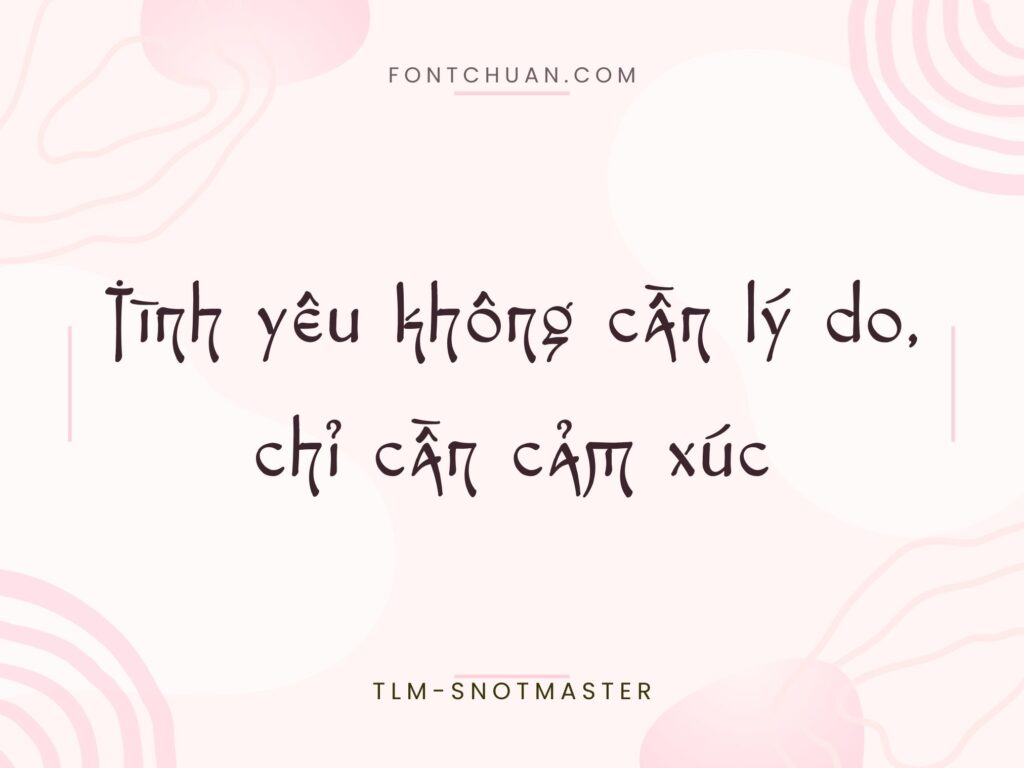
Font Snotmaster V Việt Hóa
Tác giả Font: Walter Velez
Snotmaster V là một font chữ mang phong cách Gothic hiện đại, được thiết kế bởi Walter Velez. Font này có các nét chữ độc đáo, gợi nhớ đến kiểu chữ viết tay với bút lông, tạo cảm giác cổ điển và nghệ thuật. Phiên bản Việt hóa được thực hiện bởi cộng đồng, hỗ trợ đầy đủ tiếng Việt và nhiều ngôn ngữ khác. Font được sưu tầm và đăng bởi thành viên của Font Chuẩn.
Font có thiết kế với các đường nét mềm mại, uyển chuyển, phù hợp cho các dự án thiết kế như bìa sách, thiệp mời, poster và các ấn phẩm truyền thông cần sự sáng tạo và khác biệt. Các ngành nghề như quảng cáo, giáo dục, thiệp cưới và ẩm thực có thể tận dụng hiệu quả font này. Ngoài ra, Snotmaster V cũng thích hợp cho các sự kiện như lễ hội, sinh nhật, ngày Nhà giáo và Valentine.